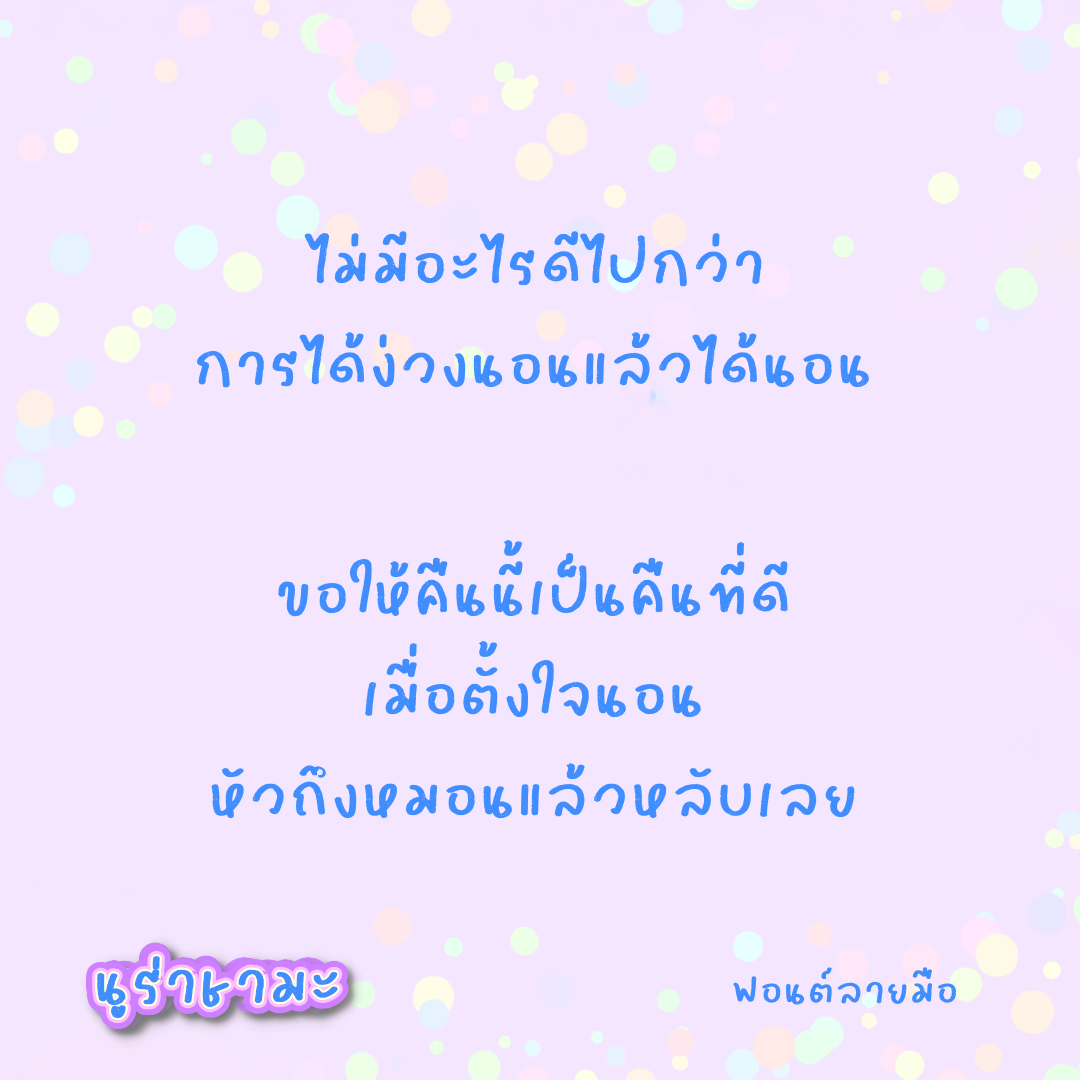
นูร่าชามะ (Nura chama)
ฟอนต์ลายมือไม่มีหัว  ตัวหนา ลายเส้นขรุขระ
ลายมือหวัดมากๆ มีด้วยกัน 3 น้ำหนัก คือ บาง ปกติ หนา นูร่าราดาเปิดให้ใช้ฟรีส่วนตัวน้ำหนักบาง นะคะ